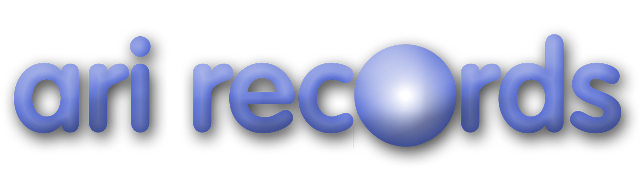
Und nen anderen Link! Ich challenge Dich jetzt, ich glaub es ist eher die Adobe-Version, schau mal das "r" an. (Das wär jetzt aber massiv Glück meinerseits, ich kannte die andere gar nicht. :D )
Freefont: Hm, die Wikipedia empfiehlt MgOpenModata als freie Alternative. Sieht allerdings ziemlich… griechisch aus. :hammer: Kannst Dir ja mal anschauen. :?